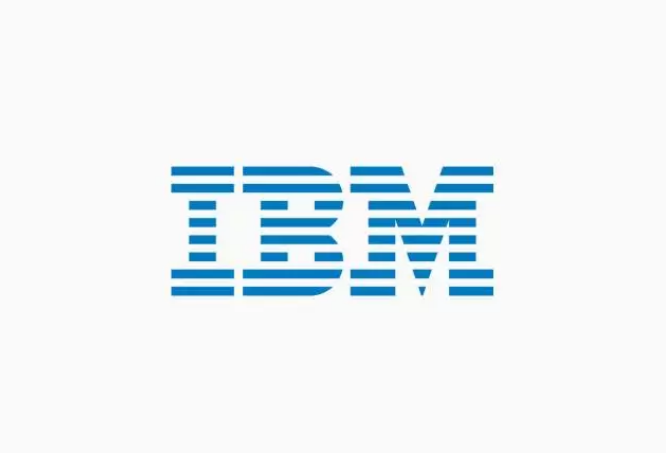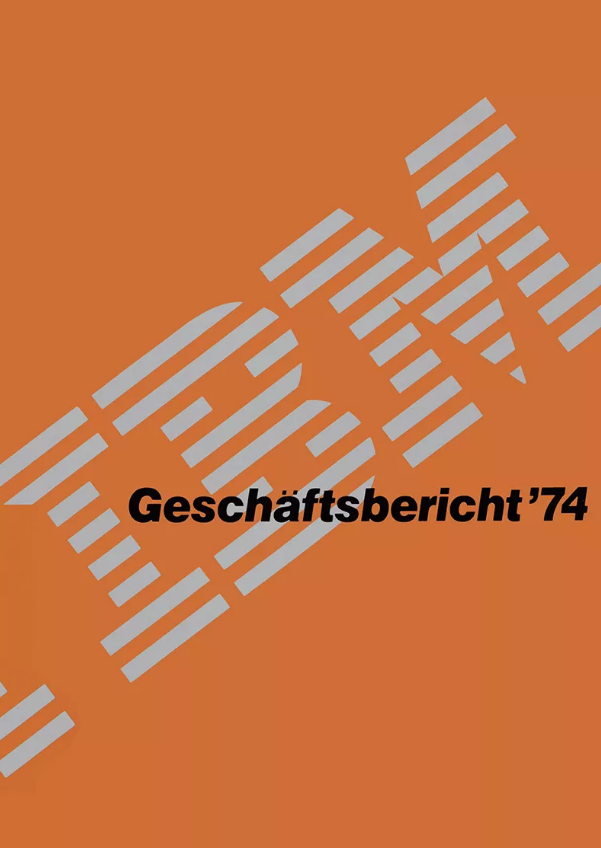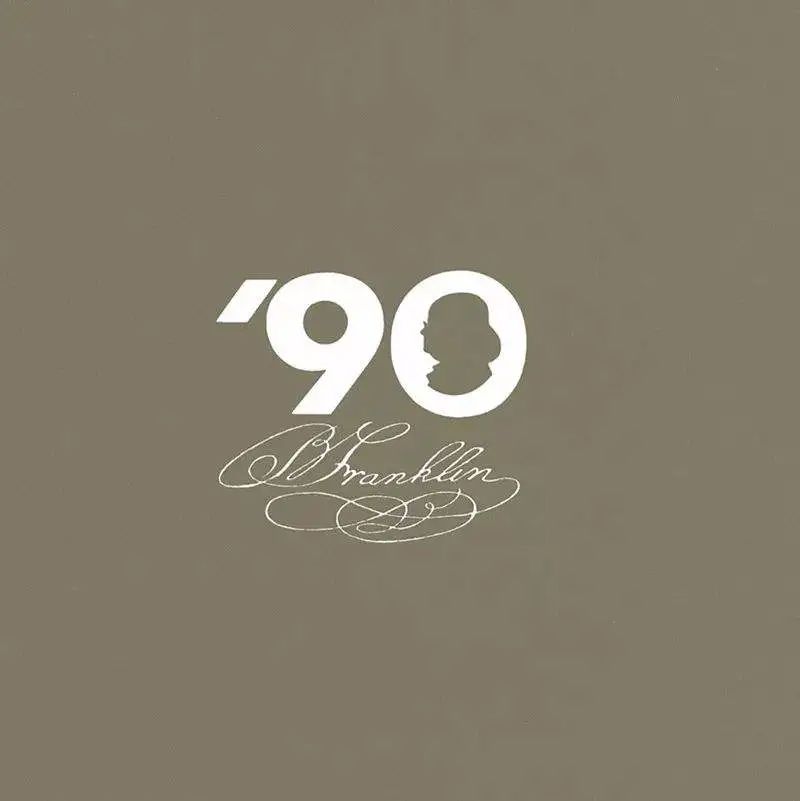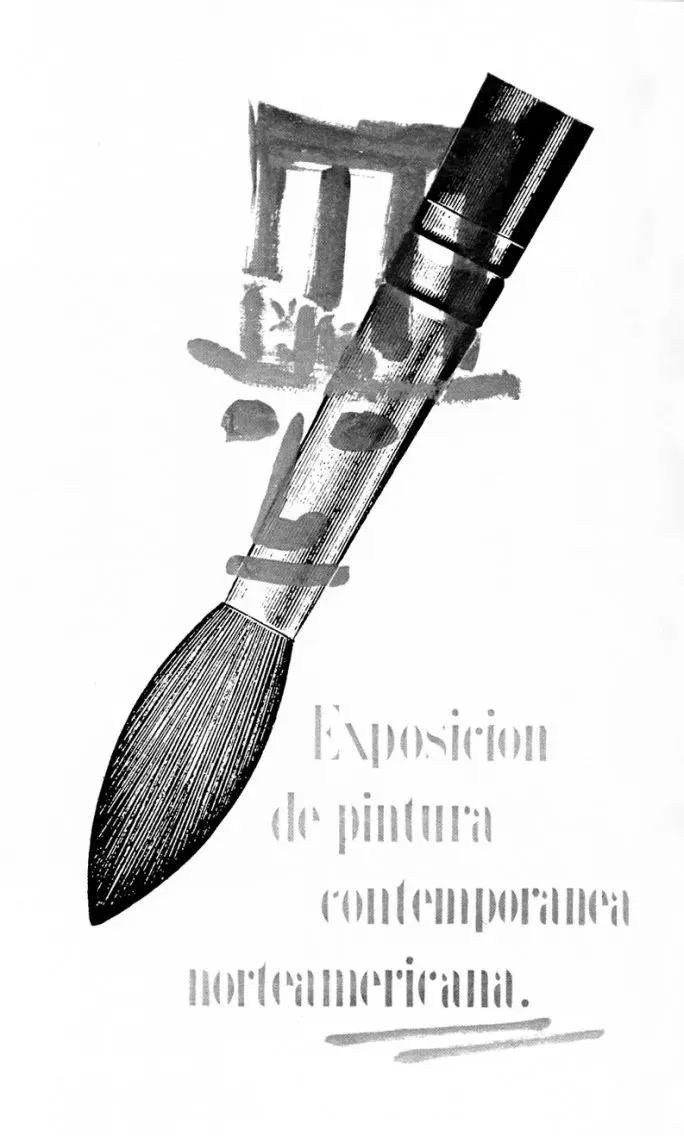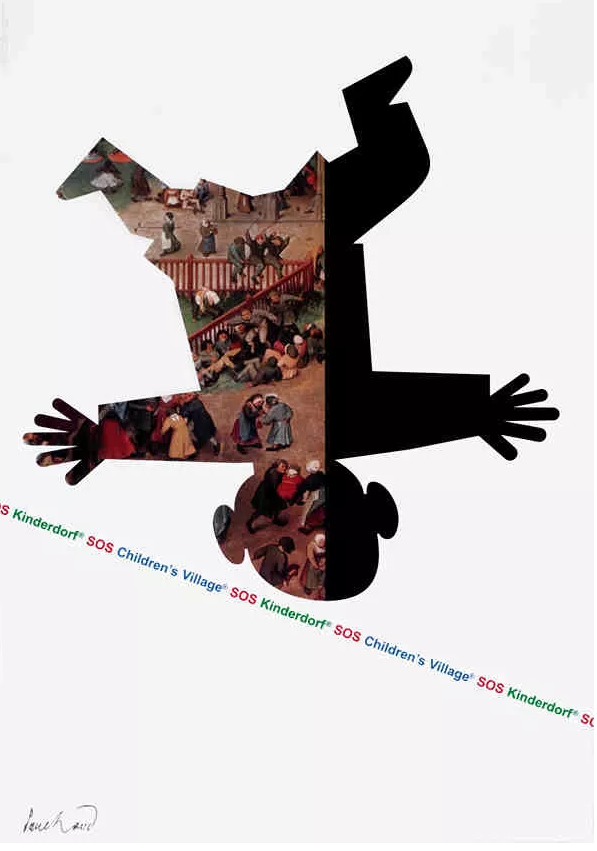
世界上最霸道的乙方设计师什么样?
敢捶桌子怒怼乔布斯
而且一口气怼了两次
一口气收10万美金设计logo
这位乙方还说着
“我从不给备选方案”
“我一稿不改”
“不管你满不满意都要给我全款”
挑剔偏执的乔布斯,竟然完全没脾气
还夸赞对方是最专业的合作方
甚至影响了乔布斯之后几十年的工作心境
是谁如此傲娇
35年前发生了什么
最牛乙方:一稿不改
1985年,种种原因,乔布斯被苹果公司赶出了董事会。
是的,被他亲自聘请来的原百事可乐CEO斯卡利,连同董事会赶走。
就是下面这位,乔布斯曾对他说过一句话,让无数人记忆深刻:你是想卖一辈子甜水,还是跟着我们改变世界。
▲乔布斯和斯卡利
后来才知道,哪来的“我们”?
乔布斯被迫离开苹果后,决定创办一家新公司,NEXT,专门对标苹果。
他打算开发做电脑,开拓大学教育市场。
第一步就是做logo,为新公司打造品牌形象。他找到了美国著名的平面设计大师,美国设计之父,保罗·兰德。学设计的小伙伴恐怕没人不知道吧。
(1914-1996)
▲保罗·兰德设计过的logo
这位老人家被称为史上最伟大的logo设计大师。他为IBM设计的logo家喻户晓。
再说,当时的IBM也是苹果的头号竞争对手。
老乔花了10万美金请保罗·兰德设计一个新logo。
作为甲乙方,两人签了合同,内容大概是:
无论最终是否使用此logo,必须付全款,且一稿不改。
一稿不改有多霸气?10万美金什么概念?当年大师一个logo能换上海好几套上百平的房子。
面对这样的“霸王条款”,脾气倔强的乔布斯也欣然接受了。
▲苹果现logo,不是保罗·兰德设计的哦
很多人奉劝他,不必花这么多钱在logo上,但老乔执意这么做。他认为一个好的标识能给公司更高的定位和形象。
苹果公司也是同理,logo造型和公司名称一致,辨识度极高,让人一眼就能记得住。省去了过多营销,降低了教导大众一遍遍认知的成本。
有了之前的成功经验,乔布斯更加断定砸重金让保罗·兰德设计logo,值。
他能接受一稿不改,但问兰德能不能多出几个方案,让他选选?
兰德一口回绝:
“我做设计从不给客户备选方案。就一个,要方案多的,你去找别人。”
“我会给你提供最好的方式解决问题,无论你最终用不用,都要把钱付给我。”
▲保罗·兰德设计的美国传播公司logo
日常暴躁且偏执的乔布斯,认为自己遇到了同道中人,没有再反驳。
两周左右的时间,logo就设计好了。最后,大概是这个样子。各位觉得如何?
因为乔布斯和他描述了未来电脑的样子,兰德将logo做成了黑色立方体。
为了满足乔布斯的意愿,他用公司名称来设计logo,他认为使用基础字体去设计logo是必要的,然后在其中一个字母上做创新。
保罗·兰德还设计了一个小册子,从字体,排版,颜色多方面论证了这个logo的合理性。乔布斯非常喜欢。
next是一个太常见的词,为了让它陌生一点,保罗·兰德将其变成大写。将其中的“e”变成小写,做出视觉焦点,有趣灵活。
寓意三个单词:education教育、excellence卓越、exceptional杰出。
据《乔布斯传》记载,他看了一会儿logo,过去拥抱了兰德。
然而他们还是存在一个分歧,兰德把字母“e”设计成暗黄色,而乔布斯希望能改成更为明亮和传统的黄色。
兰德用拳头猛击桌子说,
“我做这行已经50年了,我知道自己在做什么。”
乔布斯妥协了。
这一次合作后,对乔布斯产生很大的影响。他说,兰德的做法让人耳目一新。
他提醒每个客户都应该记住,你雇佣的是一个比你更清楚该如何解决问题的人,不要让对方给你选项。
1996年NEXT被苹果收购,但这个logo仍旧成为传世之作。保罗·兰德也在这一年离开人世。
1997年的苹果广告里,保罗·兰德占了C位,和卓别林,毕加索,爱迪生这样的天才并列。
大师的三种设计手法
IBM的logo,是20世纪品牌发展历史中伟大的成就之一,由保罗·兰德亲手设计。
谁能想到,它曾被IBM的主管疯狂吐槽,“这玩意让我想起格鲁吉亚的锁链囚犯,还有点像店铺的招牌。”
保罗·兰德曾在《设计的思考和绝望》中写道:
有多少模范作品被葬送在庸俗的吹毛求疵中?
有多少好设计,被那些对视觉逻辑一窍不通的客户瞎指挥,变成劣质作品?
老爷子确实不简单,从事设计60多年,在耶鲁大学教了30多年设计,还为各大顶级企业做商业顾问。
极简的表达
IBM最初的logo带着鲜明的强势感,保罗·兰德为了收敛视觉效果,设计了多道横纹。很有电磁波振动的动感,寓意着高科技、严谨、前卫。
▲1956年IBM的logo
▲保罗·兰德设计的新logo
他深受包豪斯理性美学的影响,讲究功能主义和实用。在他看来,好的设计应该简洁表达出内容,无须华丽的缀饰。不好的设计则徒有其表,肤浅。
“除非以最大程度的简洁和克制来进行logo设计,否则无法生存。”
拼贴艺术
保罗·兰德也被称为“平面设计界的毕加索”。
为了在平面上突破空间的限制,催生了拼贴这样的艺术手法。他将欧洲艺术家的创作方式融入进自己的领域。
刚看到的时候吃了一惊,没想到严肃的大师能做出如此可爱的设计,有童趣在里面。
他大胆使用补色对比,不同几何形状混合拼接,这是在平面领域前所未有的,他是先驱,是鼻祖。
蒙太奇手法
蒙太奇最早是建筑学里的术语,之后被用来命名电影的剪辑手法。而保罗·兰德将其放到平面设计中。
还是拿IBM来举例,眼睛替换掉“I”,寓意对人的关爱。B变成了蜜蜂,象征勤奋。M依然代表科技感。
《Eye-Bee-M》IBM 海报
他有段时间沉浸在蒙太奇艺术手法中,不用简单字母做平面设计,而是把符号进行分解重构。
抛开极简设计的冰冷感,使用蒙太奇手法的平面设计,带了一些神秘的感性。
保罗·兰德曾说,市面上的logo越来越多,糟糕的设计也层出不穷。原因有三点,管理层对优秀设计的忽略和无知;设计师能力或话语权不够,导致大多数人把设计师当成美工。
一个好的Logo无法让一件低劣的产品变得更好,却能让一件优良的产品引人注目。
没想到早在20多年前,大师就已经预测到当今现状。
象君一直认为做logo设计的人很牛b,寥寥几笔就能精准传递品牌的魂。
看似简单,背后却有巨大的投入,训练,咀嚼,理解。下次谁再说:麻烦帮我免费画个logo。